中国相信字如其人,所以大人们总爱说,“写字就要端端正正地写,做人要堂堂正正地做。中国人有大气的诗意,全在汉字的想象里。藏在黄河白云间、浔阳秋瑟中;孤城的羌笛声中,空山的新雨里。一笔一划的字体,藏着我们共有的文化基因特质。今天要给大家介绍的就是几款蕴含着中华文化的方正大方的字体,接下来和小编一起看下面字体图片了解这些字体吧~
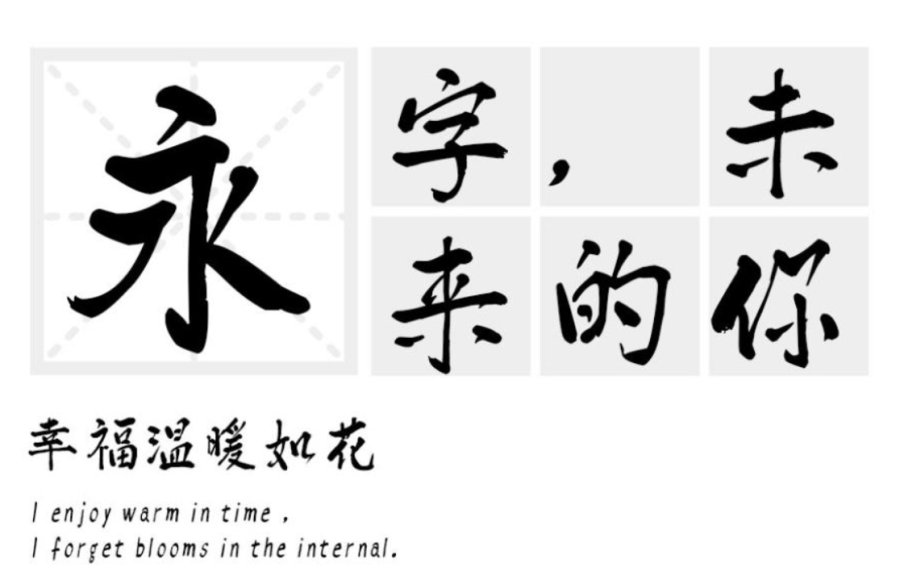
这款“汉标清新洒脱体”运笔舒展飘逸,部件排列别具一格,韵味缠绵,恍如初见心动一刻,呼之欲出的雀跃感受。适用于文艺类的书刊、品牌广告和产品包装设计,以及社交网络的个性化用字。
“汉标熟宣毛笔体”这是一款带有书法味道的纯手写字体,将隶书与楷书笔画相结合,字型偏方,笔画中也减少了过多的处理和笔势,厚重、饱满。因为是纯手写的原因,它独特的气质更与其他字体不同,看似统一,其实各有各的味道,每个字都可以独具风情。字由字在,大到自然,便是对它最好的诠释。